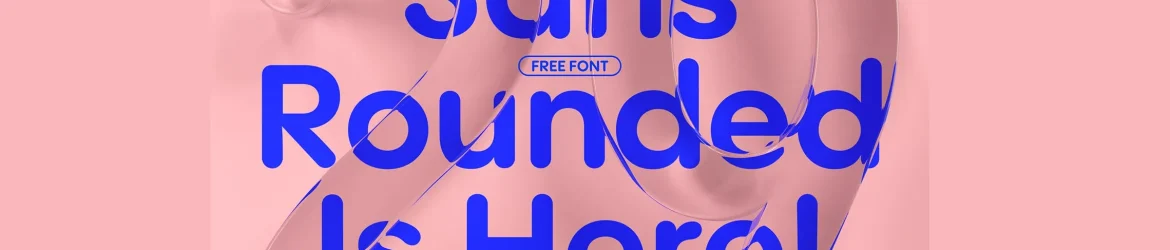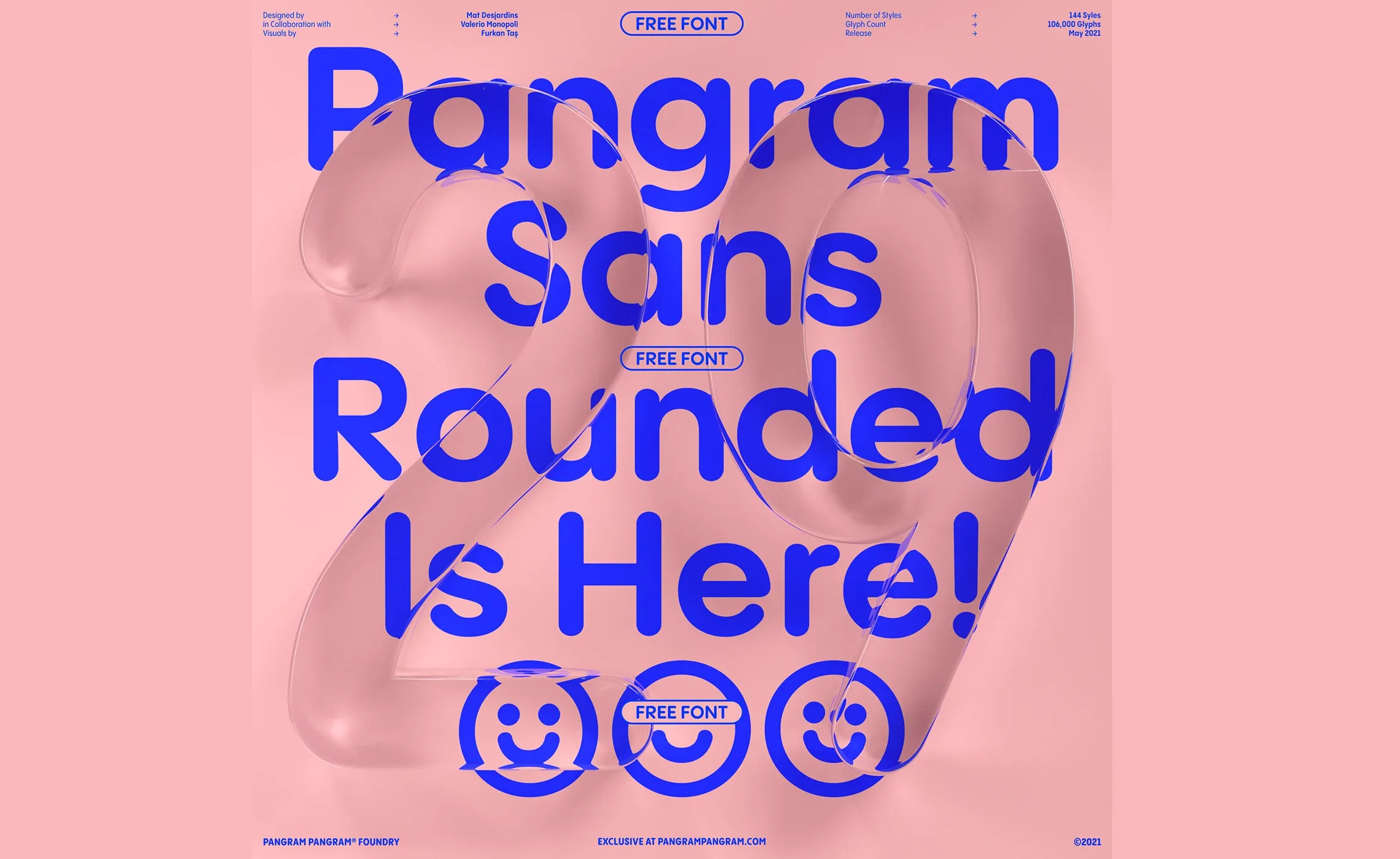
Pangram Sans Rounded Font Family – Fonte Grátis
Pangram Sans Rounded Font Family
Esta é uma família de fóntes geométricas arredondadas criada pelo designer Pangram. Ela mantém sua força e extensibilidade enquanto se torna mais acessível, com 144 estilos disponíveis. Suas variações mais fortes permitem que o tipo se torne único em seu jeito distinto. O famoso alfabeto cirílico também está incluído para quem deseja uma versão ainda mais robusta dos designs desta família de fontes. Esta família é perfeita para aqueles que buscam um arredondamento sofisticado nas suas criações, sem abrir mão da elegância e modernidade do tipo geométrico. Com 770 caracteres por estilo, este tipo permite uma grande variedade de opções, inclusive com várias combinações de Estilo Personalizado. Suporte a idiomas como os dos Estados Unidos, Europa e cirílico. Acredite, esta famosa família de fontes pode se tornar seu querido “go to” em qualquer design gráfico que você faça no futuro.